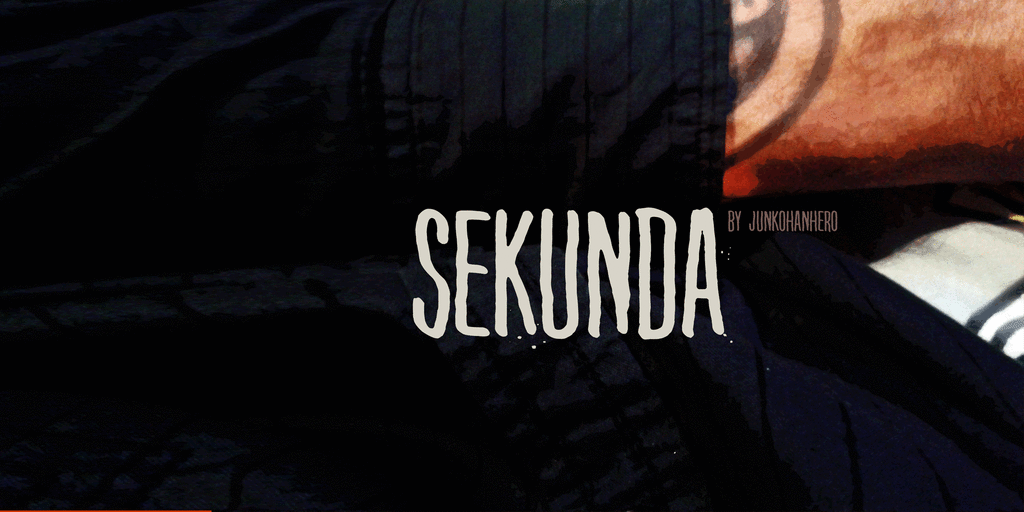
Estamos muito felizes por você ter descoberto a nossa fonte “Sekunda Font”. Inspirada no estilo retro dos anos 80 e 90, esta fonte é uma excelente escolha para dar um toque nostálgico a qualquer projeto de design pessoal. Crie cards de vídeo divertidos ou encontre-a perfeitamente em suas criações de design gráfico moderno. Quer usar “Sekunda Font” em seus projetos comerciais? Não há problema algum! Temos uma licença comercial para você adquirir. Basta enviar 15€ por Paypal e enviar um email. Também podemos te ajudar com a compra através do botão de doações, que fica bem perto da caixa de download. Esta fonte foi criada pelo designer Hamilton, um dos nossos talentosos membros de equipe aqui na Cloud. É uma maneira maravilhosa para você expressar sua personalidade e se destacar no mercado dos designs digitais, seja em seu próprio negócio ou simplesmente como hobby. Sua escolha de adquirir nossa fonte é um investimento valioso não só em termos financeiros, mas também na experiência criativa que ela oferece ao seu design. Obrigado por sua compreensão e pela preferência para “Sekunda Font”.